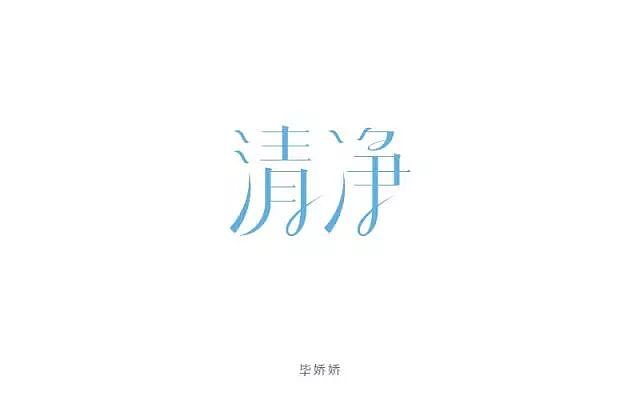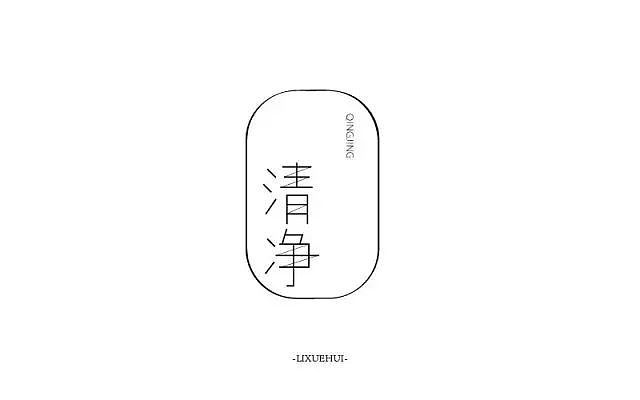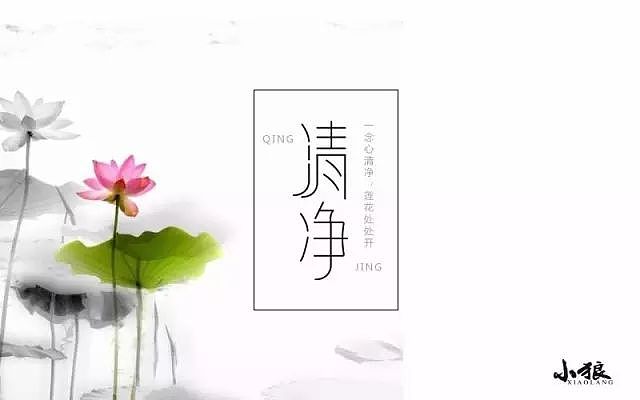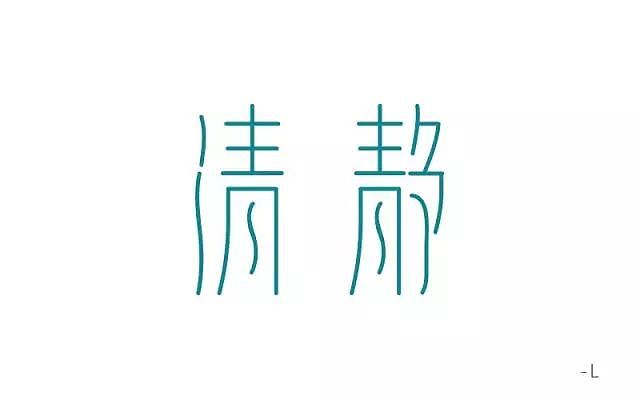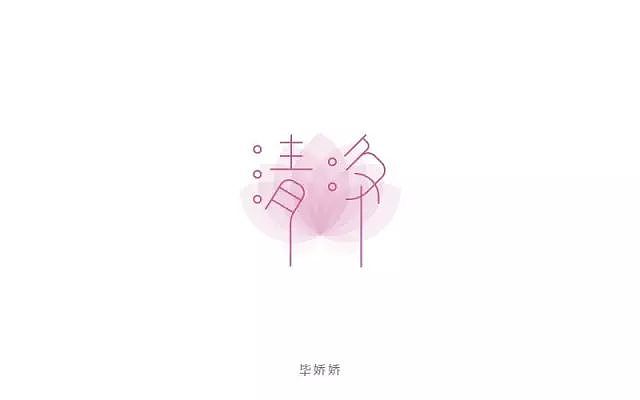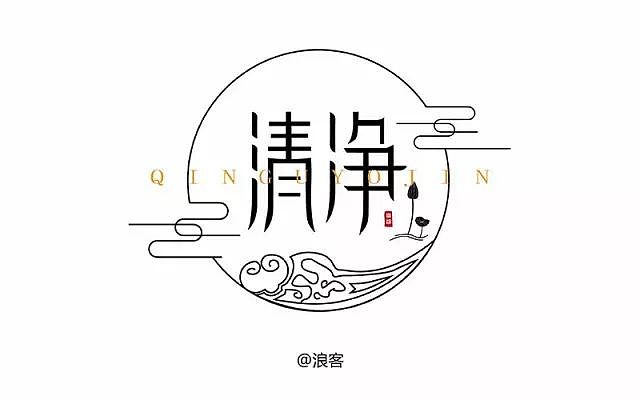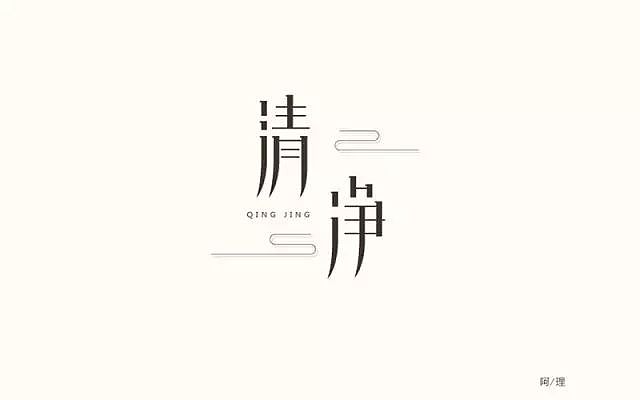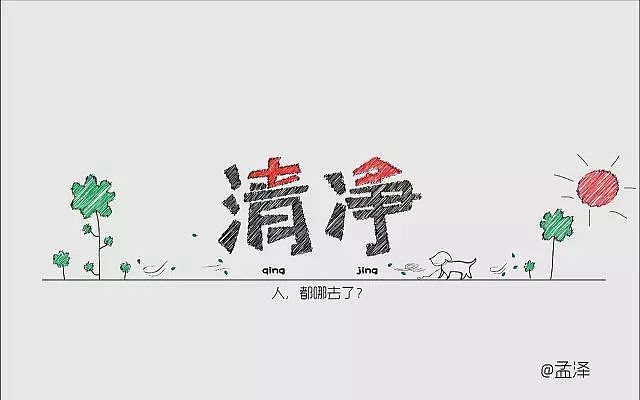
笔画粗细有问题,如清字左上角的两点,净字上面的两点都明显偏瘦弱;
这个作品,不说字的问题,也不说排版的问题,就说这一点:圆角矩形明显没有图片居中,请原谅我的强迫症;
笔画变形很别扭,很不流畅,如清字左侧三点;
还有,把配图去掉;
首先,是清净,不是清静,做错字了;
两个字中,月字旁的设计变形是不错的,但清字左侧三点水和静字右侧“争”的部分,都需要收敛一点,目前略夸张,不平稳;
清字右下角,月字的倾斜,并不耐看;
净字明显变形过度;
为了变形而变形,很有可能导致字体面目全非。
清字,右侧部分,上面的宽度和月字的宽度待调整;
净字,右上角的短竖线明显偏细;
整体排版和元素搭配,也偏复杂;
经肉眼显微镜观察,“青”的上面,三横的长度不准确;
净字,左上角偏空,点应该上移;
没有表现清净之意,太复杂;